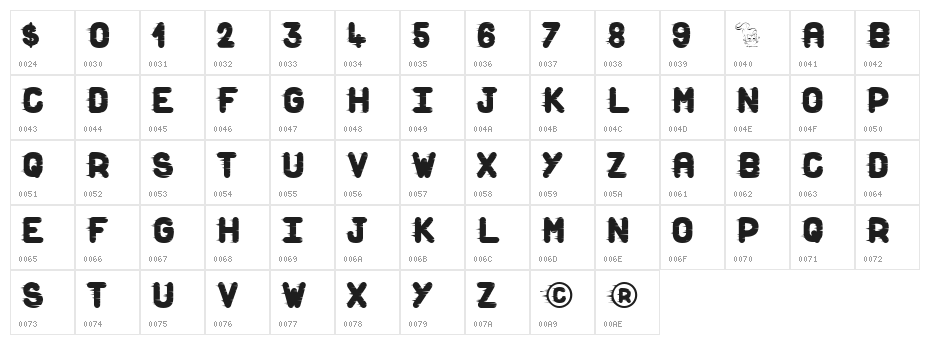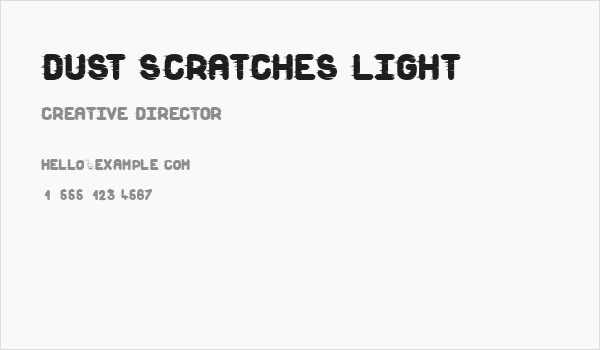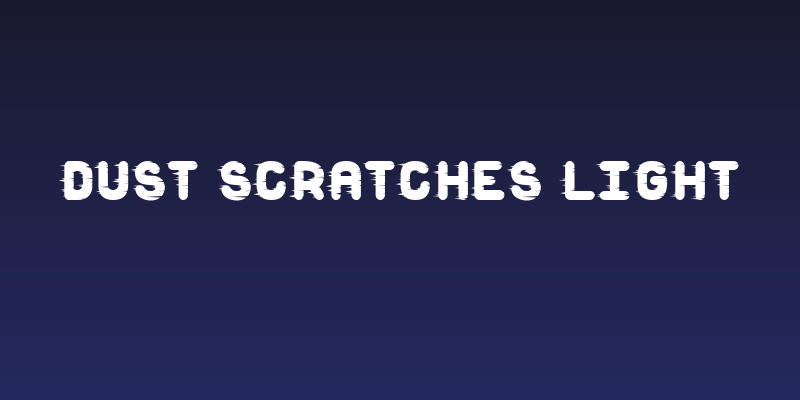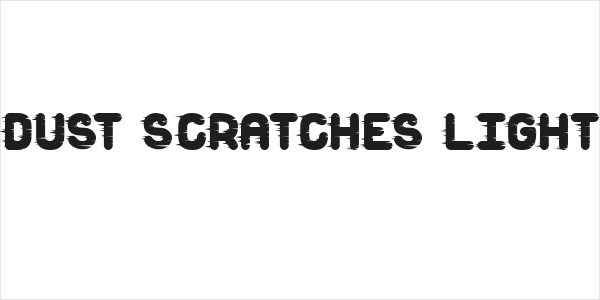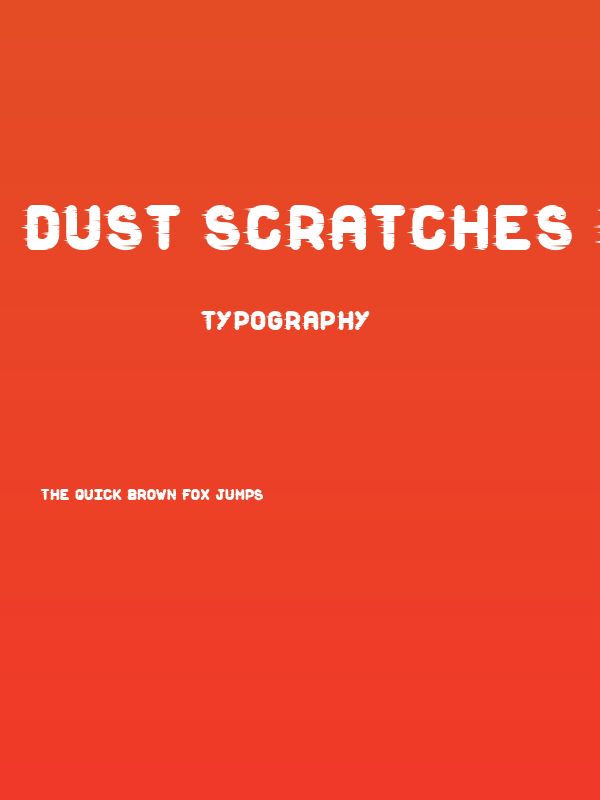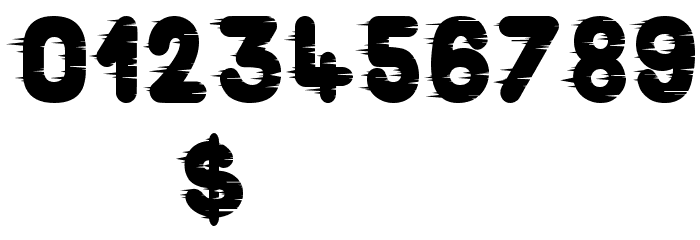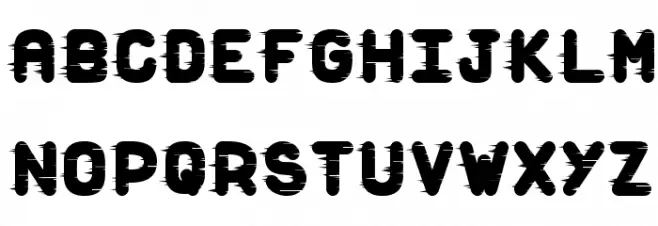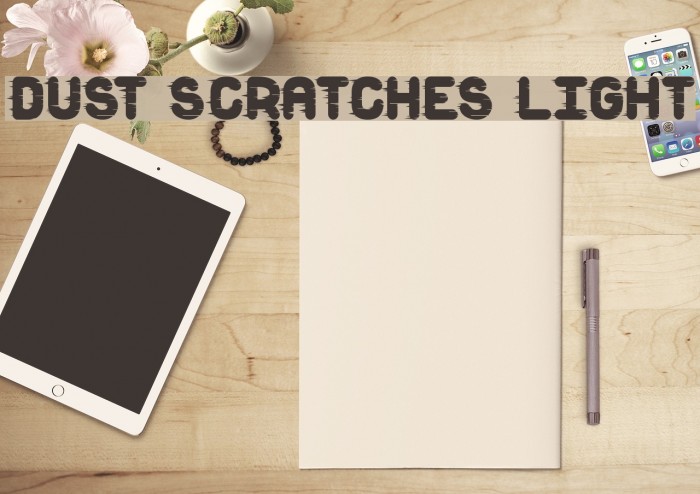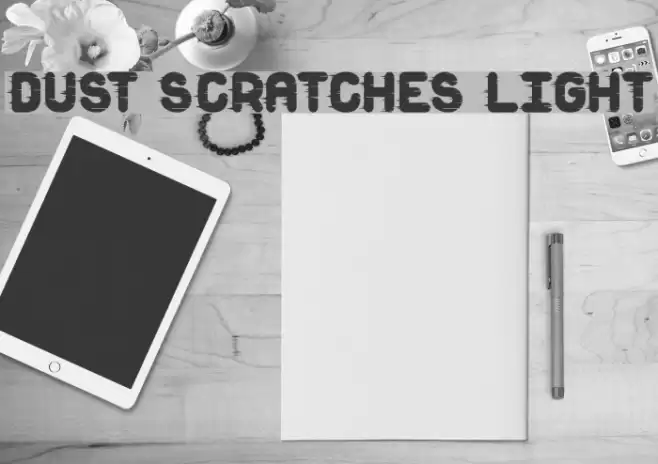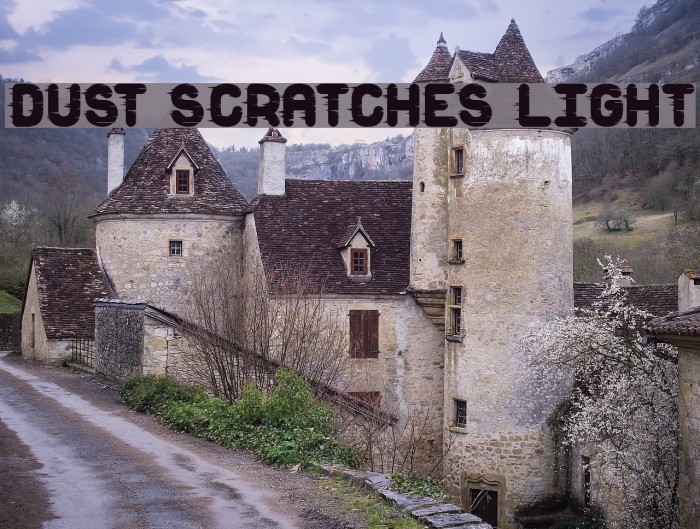
Dust Scratches light Font
✎ Distorted Eroded
| Категория | Distorted Eroded |
| Общий стиль | Grunge, Edgy, Distressed |
| Рекомендуемые проекты | Ideal for album covers, posters, urban-themed designs, and branding that requires a gritty, edgy look. |